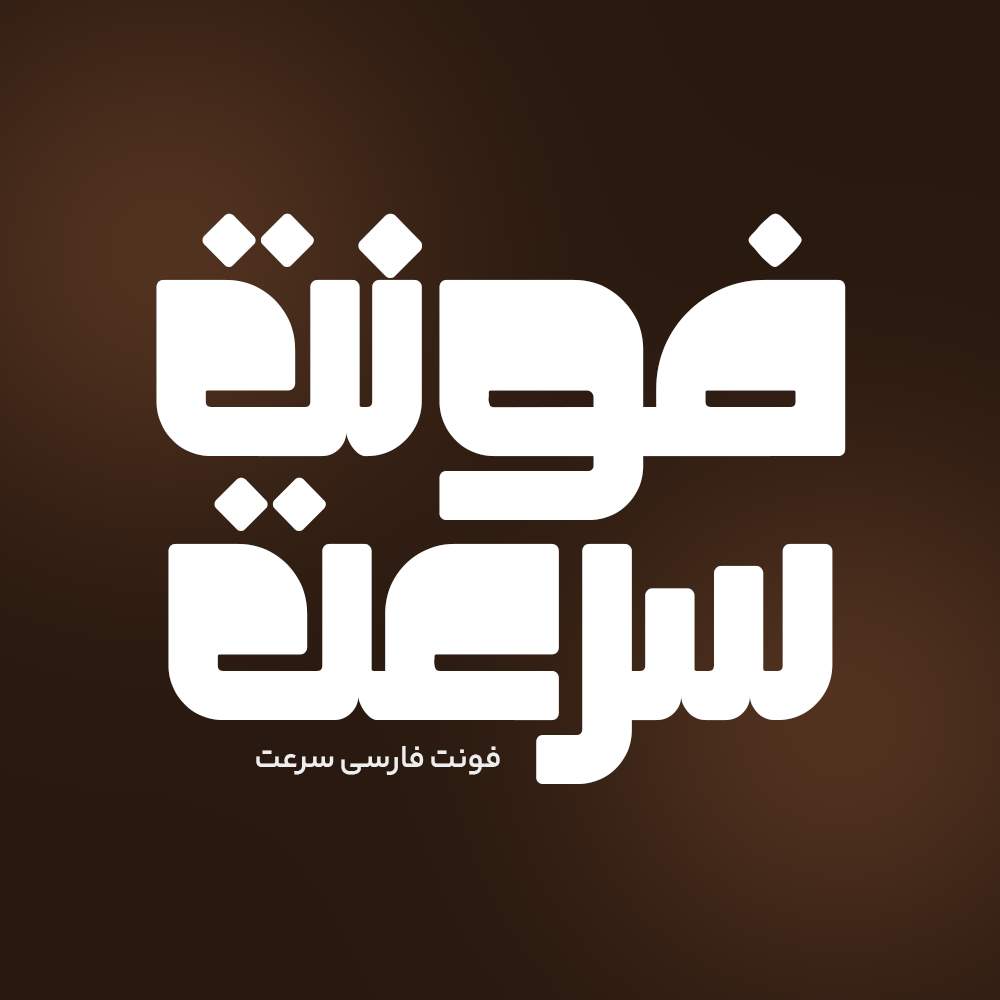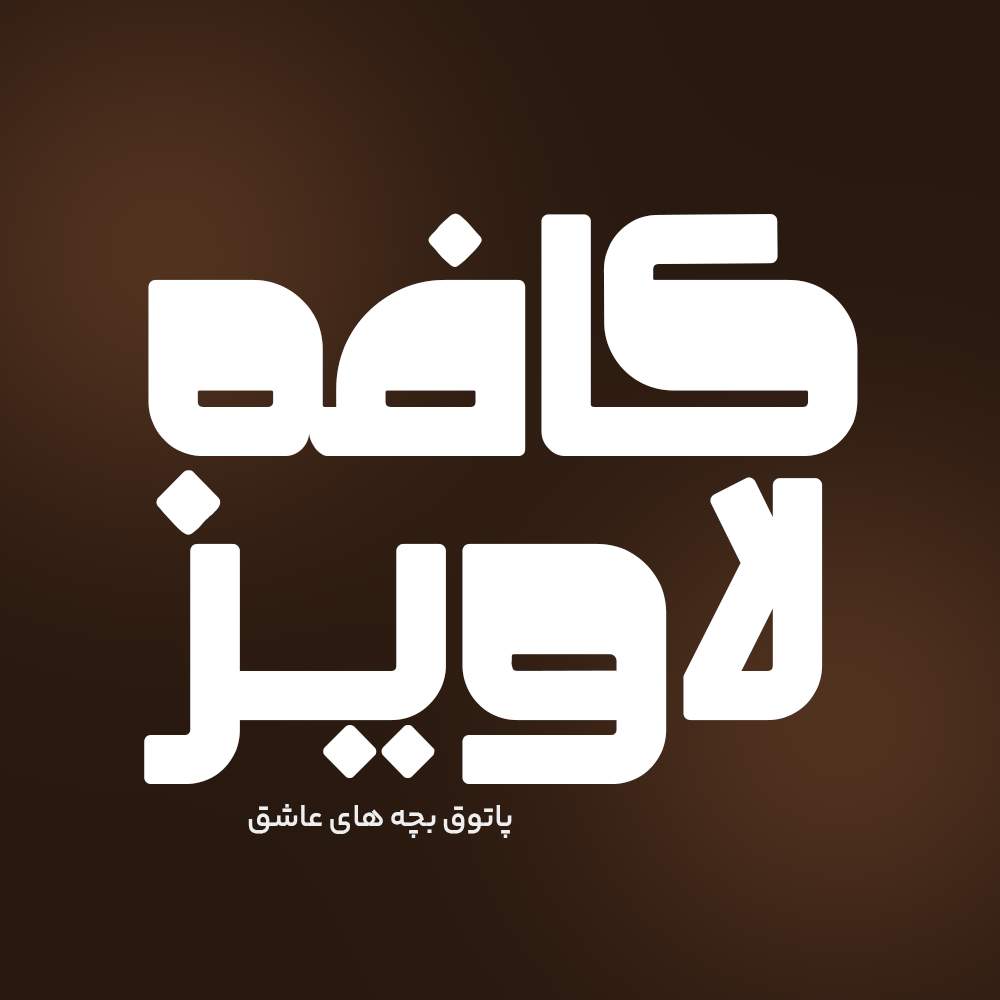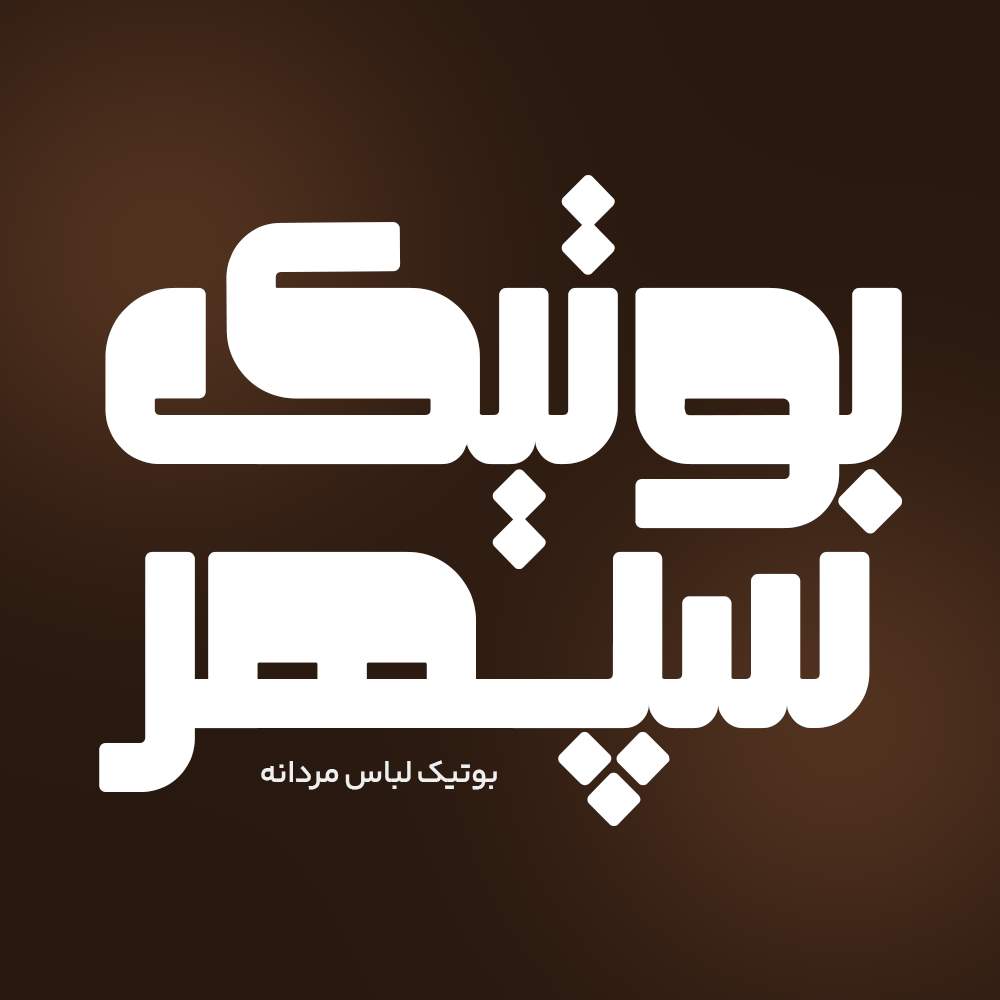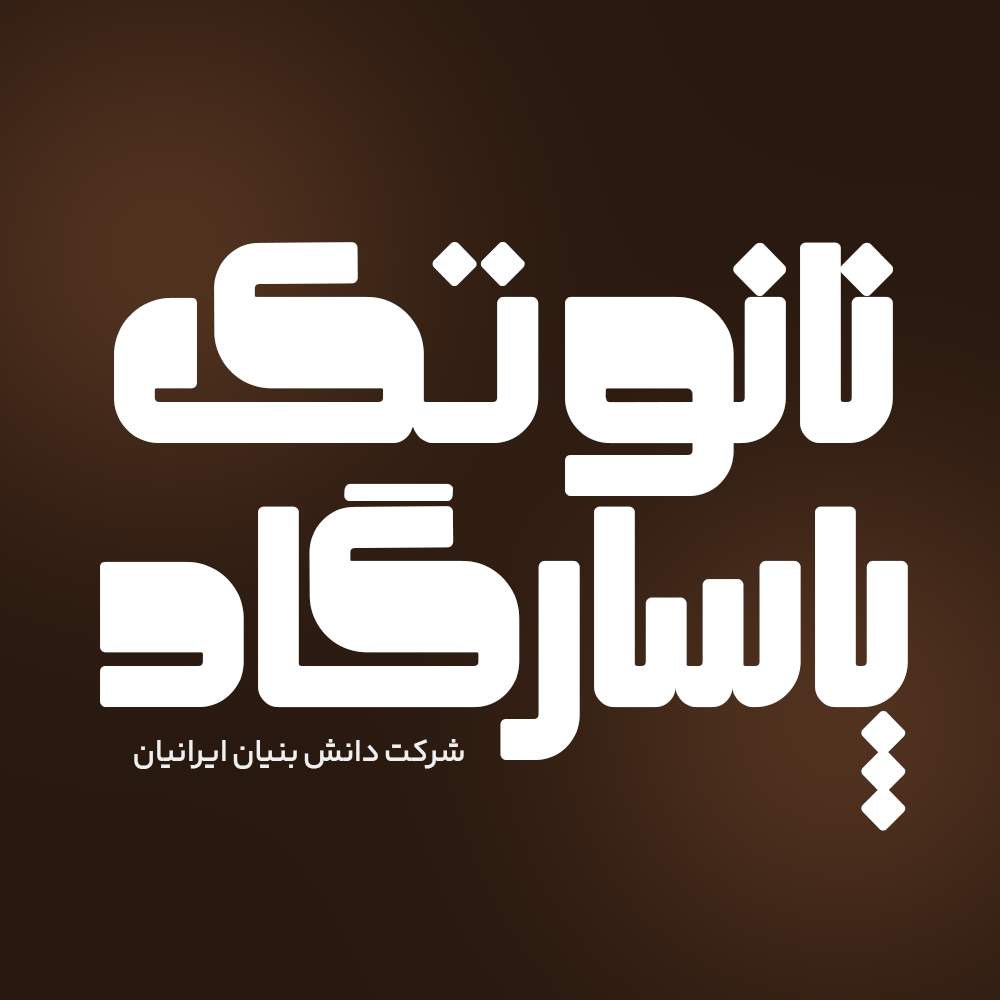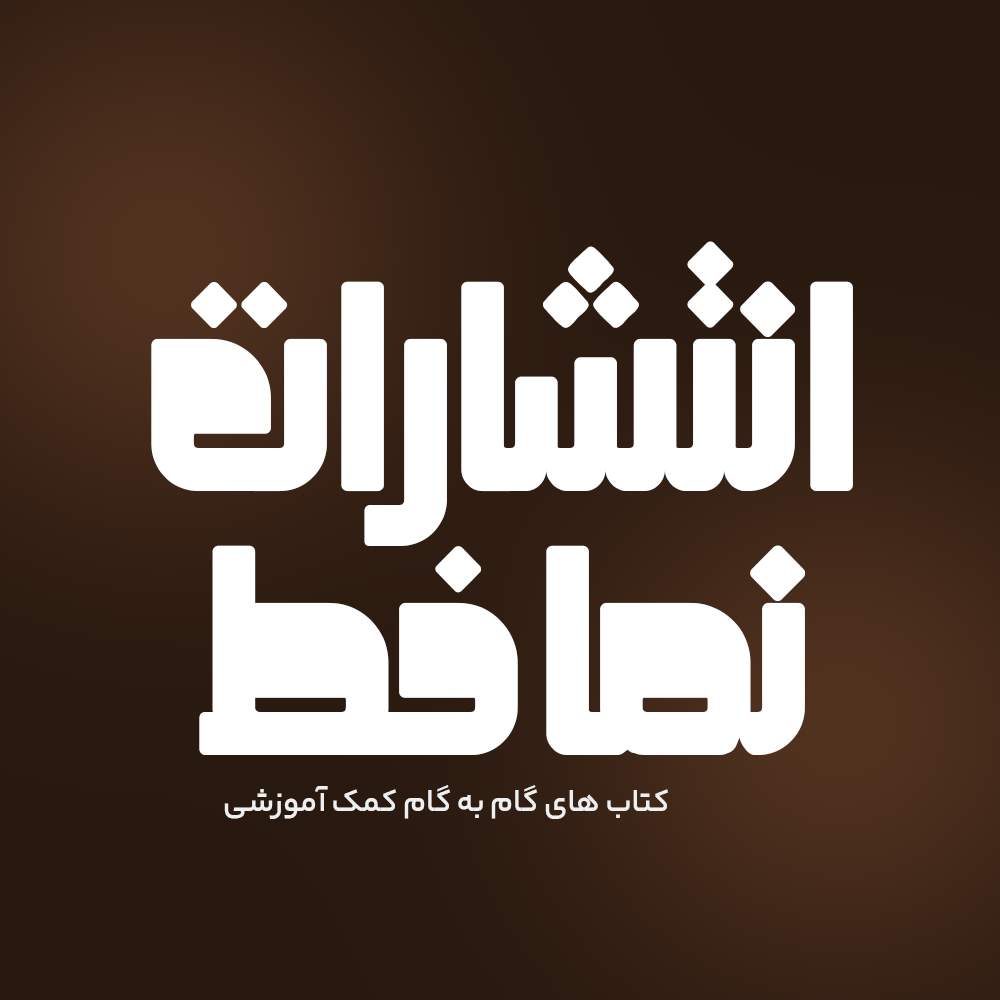
فونت فارسی سرعت Sorat Font
فونت فارسی سرعت از دسته فونتهای فوق سنگین با بدنه قطور است. تفاوت اصلی فونت سرعت با دیگر فونتهای این دسته، هندسه ساده و کنتراست ضخامت…
فونت فارسی سرعت از دسته فونتهای فوق سنگین با بدنه قطور است. تفاوت اصلی فونت سرعت با دیگر فونتهای این دسته، هندسه ساده و کنتراست ضخامت حروف است. فونت سرعت به سادگی در نرم افزارهای تحت ویندوز از جمله مجموعه برنامه های فتوشاپ، کورل، آفیس، اینشات و… قابل اجرا میباشد. طراحان وب سایت و گرافیست های خلاق می توانند از این فونت زیبا فونت در طراحی پروژههای تبلیغاتی و تجاری خود کمک بگیرند. در ادامه برای شما نمونه تایپ های این محصول حرفه ای رو آماده کردیم که میتوانید مشاهده کنید.
پیشنمایش و نمونه تایپ های فونت سرعت